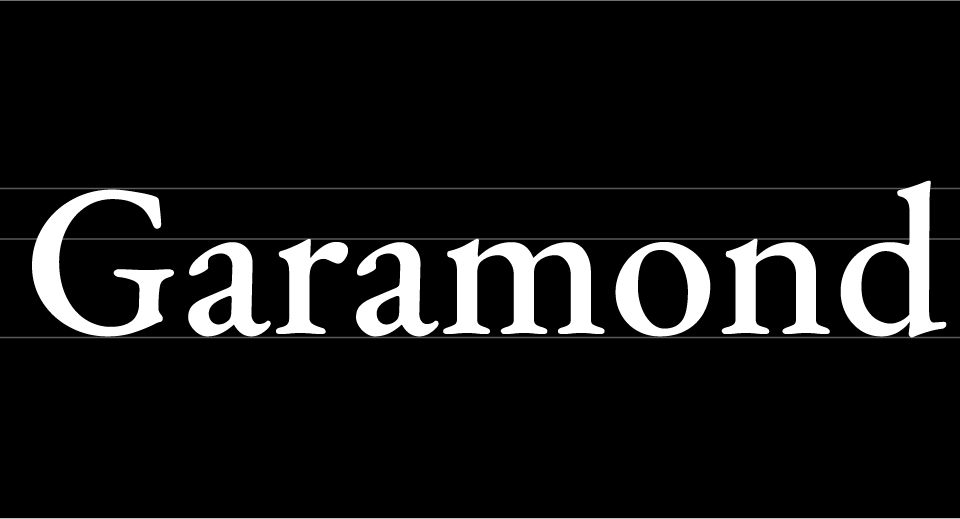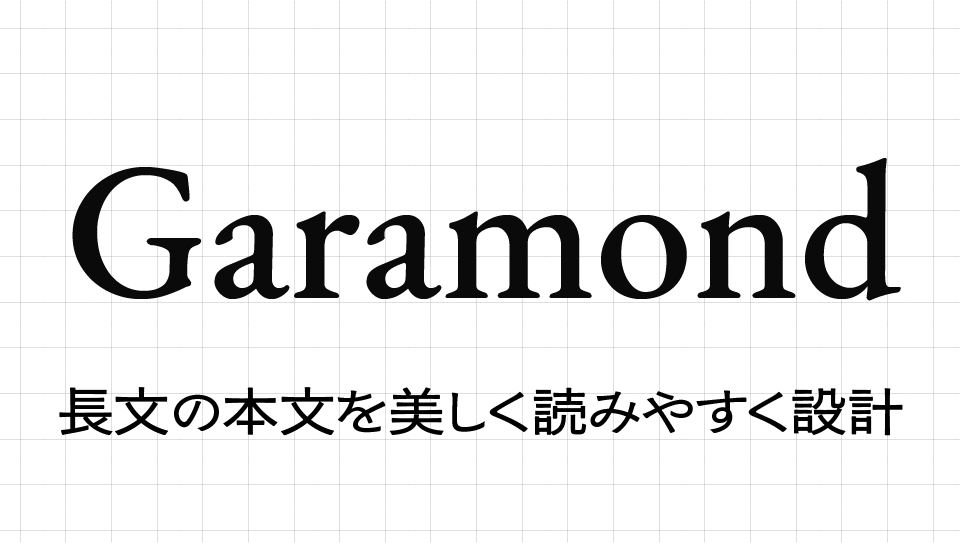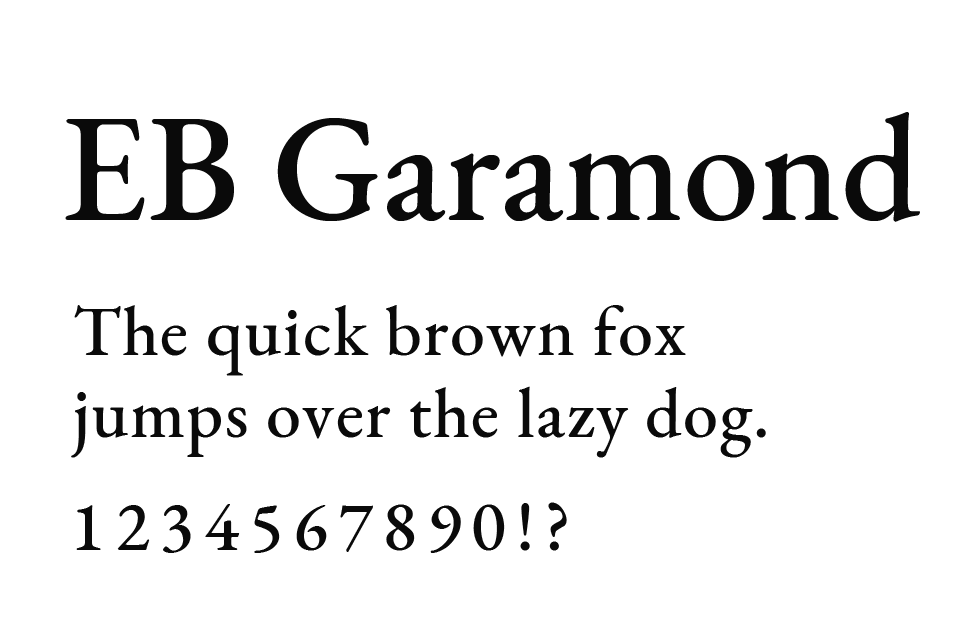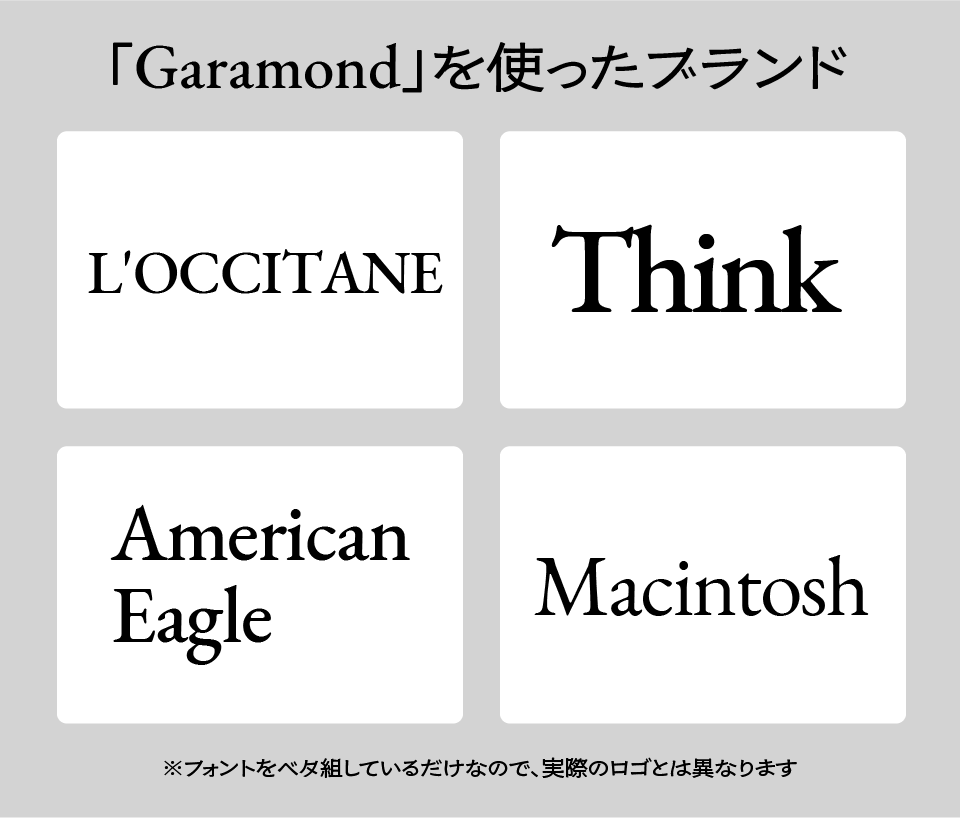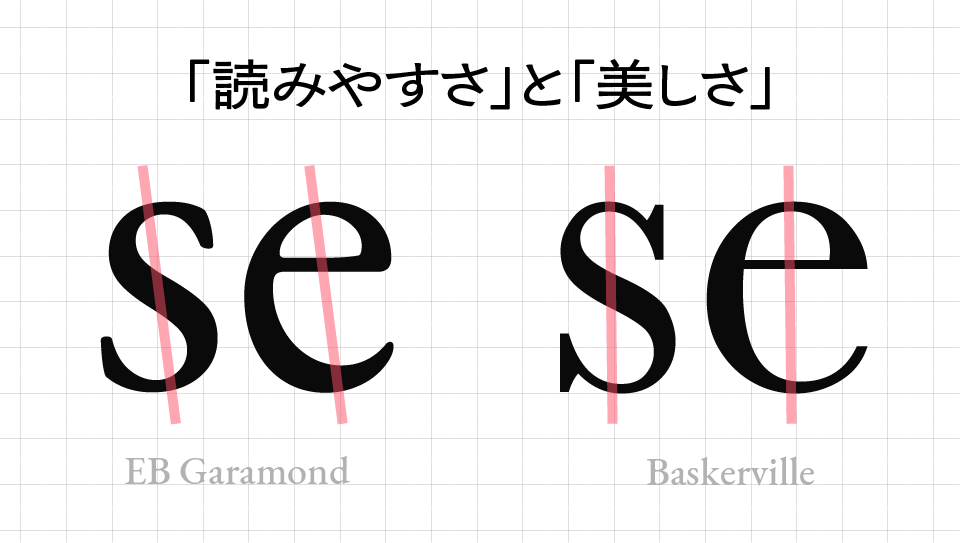
Garamond(ギャラモン/ガラモン)フォントの魅力とは?文学と歴史が息づく優雅な書体
静かで、気品にあふれ、知性を感じさせる。そんな印象をもたらすフォント「Garamond(ギャラモン/ガラモン)」は、印刷文化の黎明期から現代に至るまで、数多くの書籍や出版物に用いられてきた、最も歴史ある書体のひとつです。読みやすさと美しさを兼ね備えたその佇まいは、まるで書物の香りや紙の手触りまで伝えてくるかのようです。
この記事では、Garamondの成り立ちと歴史、デザイン上の特徴、代替フォント、実際の採用事例などを通して、このフォントがなぜ今もなお世界中で愛され続けているのかを深掘りしていきます。
Garamond(ギャラモン)とは
Garamondは、16世紀フランスの活字職人クロード・ギャラモン(Claude Garamond)の名を冠したセリフ体フォントです。彼が制作した活字書体は、当時の印刷技術を前提に設計されながらも非常に洗練されており、のちのヨーロッパの印刷文化に大きな影響を与えることになります。
現在「Garamond」と呼ばれているフォントは、ギャラモン本人の設計だけでなく、彼のスタイルに影響を受けた後世の職人たちによる再解釈を含んでおり、Adobe Garamond、Stempel Garamond、ITC Garamond など複数のバリエーションが存在します。いずれもクラシカルで優雅な雰囲気を持ち、紙媒体における本文組みを美しく見せる代表的な書体です。
Garamondの歴史と背景
Garamondの誕生は1500年代前半。印刷技術が普及し始めた時代に、読みやすく美しい書体が求められるようになったことから、ギャラモンはラテン語文書や古典書のための書体を制作しました。
彼の書体は、当時のローマン・タイプ(古代ローマ碑文をベースにした書体)の流れを汲みながら、より抑揚とリズムを強調したものとして評価されました。
17世紀以降、彼の活字はフランス国外にも広まり、イギリスやドイツの印刷業界でも重宝されるようになります。その後も何度もデジタル化され、多くのバリエーションを生んでいることからも、いかにそのオリジナルが完成度の高いデザインだったかが伺えます。
Garamondの特徴
Garamondは、長文の本文を美しく読みやすく見せるために設計されたフォントです。セリフ(文字端の装飾)は細く繊細で、線の太さには明確なコントラストがあり、視線を自然に文章の流れへと導いてくれます。
文字の形状にはゆるやかなカーブが多く、全体として有機的な柔らかさと優雅さが漂っています。
また、xハイト(小文字の高さ)は控えめで、文字間の空間にもゆとりがあるため、ページ全体が落ち着いたリズムで整います。過剰な主張をせず、あくまで「読みやすさ」と「美しさ」のバランスを重視したデザインであることが、文学作品や教科書、学術書などに長年採用され続けている理由でもあります。
類似・代替フォント
Garamondは有償で提供されるフォントも多いため、プロジェクトによっては代替フォントの検討が必要です。以下に代表的な類似フォントをご紹介します。
Times New Romanはやや堅さがあるものの、本文用途では似たような雰囲気を持ちます。Google Fontsで無料提供されている「EB Garamond」は、クラシックなGaramondのスタイルを忠実に再現しており、デジタル環境でも扱いやすいバリエーションです。
また、CormorantやCardoといったオープンソースフォントも、Garamond的な品格とリズムを持っており、書籍調のデザインに最適です。
Garamondが採用された代表的な事例
Garamondは、多くの高級ブランドや学術出版社、文学系の書籍などで広く使用されています。中でも有名なのは、Appleがかつて広告やマニュアルにGaramondを用いていたことです。特に、スティーブ・ジョブズが好んだ書体として知られ、Macユーザーの間でも印象的な存在となりました。
また、Penguin BooksやHarvard University Pressなど、知性や伝統を重視する出版物においても定番の本文書体として長年使用されています。墓碑やモニュメントの刻字にも使われることが多く、時代を超えた“残す文字”としての信頼性も高いフォントです。
Garamondを使うときの注意点
Garamondは繊細なデザインが魅力である反面、モニター上や小さなサイズで使用すると、細部がつぶれてしまうことがあります。特に低解像度の画面やWeb上では、読みづらさを感じる場面もあるため、サイズや文字間の調整を丁寧に行う必要があります。
また、現代的なデジタルデザインにおいては、やや古典的に見える可能性もあるため、シンプルなUIやスタイリッシュなレイアウトでは浮いてしまうこともあります。Garamondを使う際は、媒体やデザイン全体との相性をよく見極めることが重要です。
Garamondは、文字を「読む」ことの喜びを思い
Garamondは、ただ情報を伝えるための文字ではありません。ページを開いたとき、そこに並ぶ文字列が美しく、静かに語りかけてくるような感覚。読むことが「行為」から「体験」に変わるような、そんな豊かさを宿しているフォントです。
このフォントを使えば、文章が持つ世界観や余韻までも引き立てることができます。派手さはありませんが、深みがある。もしあなたが、文章を丁寧に届けたい、読む時間そのものを豊かにしたいと願うなら、Garamondはまさにその願いに応えてくれる書体です。